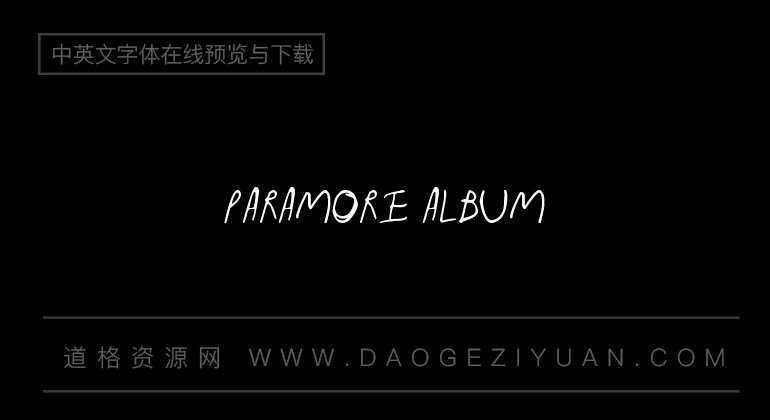
Paramore是一支来自美国田纳西州的摇滚乐队,他们在不同的专辑中使用了不同的字体。 1. All We Know Is Falling (2005) - 这张专辑使用了一种非常简单的字体,看起来像是手写的。字体的颜色是红色和黑色,并且经常出现在黑色背景上。这个字体的效果很好,因为它使得整个专辑看起来非常干净和简单。 2. Riot! (2007) - 这张专辑的字体比上一张专辑更加复杂。字体的颜色是白色和黑色,经常出现在多彩的背景上。这个字体看起来非常流畅,但也有点粗糙的感觉。这个字体很好地反映了这张专辑的音乐风格,充满着能量和冲击力。 3. Brand New Eyes (2009) - 这张专辑的字体看起来更加成熟和稳重。字体的颜色是红色和黑色,经常出现在白色背景上。这个字体看起来比 Riot! 更加细腻,但也有一些简洁的感觉。这个字体很好地反映了这张专辑的主题,强调了自我探索和成长的过程。 4. Paramore (2013) - 这张专辑的字体看起来非常简单,但也非常独特。字体的颜色是白色和黑色,经常出现在红色和粉色的背景上。这个字体看起来非常流畅,但也有一些简单的感觉。这个字体很好地反映了这张专辑的主题,强调了对自我和情感的探索。 总的来说,Paramore在不同的专辑中使用了不同的字体,这些字体都反映了他们音乐的风格和主题。无论你是 Paramore 的粉丝还是设计师,这些字体都是值得研究的。内容介绍
Paramore Album是一款非常不错的手写艺术字体,具有很好的视觉感,适合于文化类的宣传设计、商业类品牌的广告和产品包装设计以及个性化文字排版等较多场景。